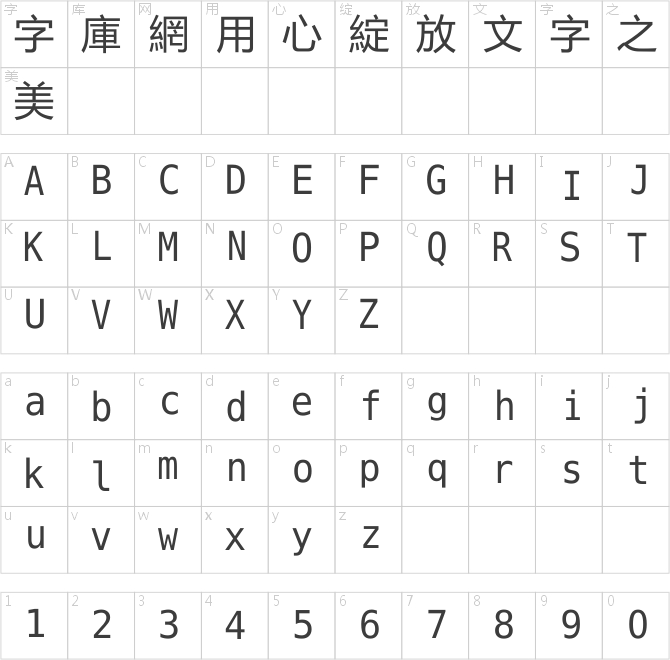
字體名稱: 正體Zfull
正體Zfull-BIG5
正體Zfull-BIG5字體字庫(kù)是一款讓人賞心悅目、百看不厭的中文字體,適合各類廣告和產(chǎn)品包裝設(shè)計(jì)應(yīng)用,字體大小17.78MB,格式為ttf字體,上傳用戶是眾聯(lián)齊成,作者/版權(quán)方為未知